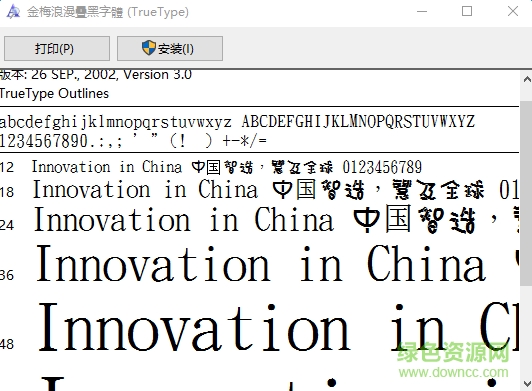
金梅浪漫疊黑
金梅浪漫疊黑字體是一款很有特色的電腦字體,這款字體寫出來(lái)的字不是那么呆板的,而且是越看越好看的類型,大家可以將這款字體用在很多方面,有需要的朋友可以來(lái)綠色資源網(wǎng)下載。
這是一款很好看的具有藝術(shù)風(fēng)格的字體,小編一般會(huì)將這種字體用在圖畫制作上面,給圖片增添活力,大家也可以試試哦。